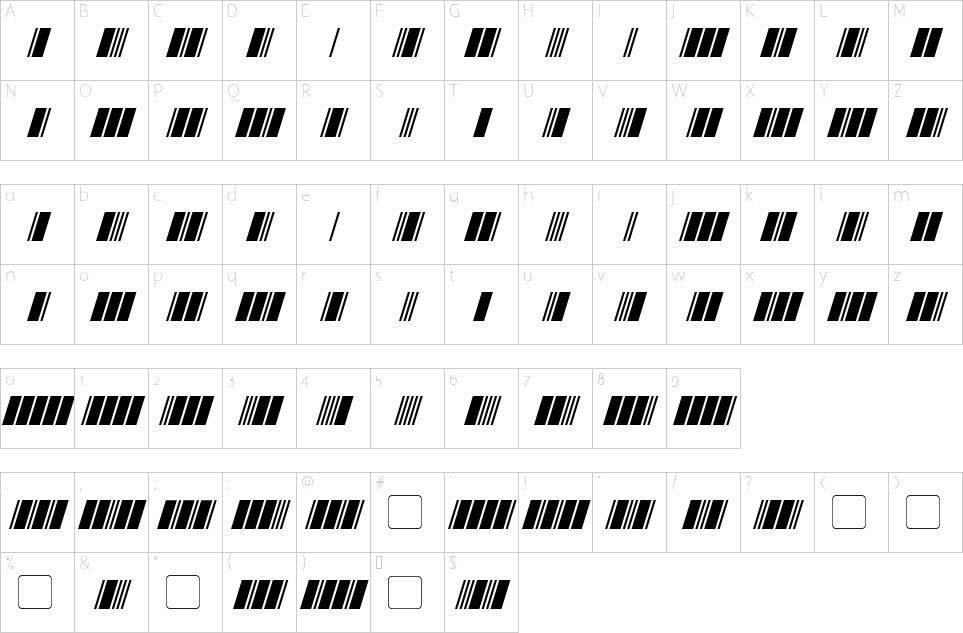
A Morse Tech Font é uma elegante escolha para designers e criadores de conteúdo digitais, especialmente aqueles que buscam uma fonte moderna e minimalista. Criada pelo designer Pixel Sagas – Neale Davidson, esta fonte proporciona um acabamento clean e sofisticado, ideal para aplicativos de notícias, sites de tecnologia e outras plataformas digitais. Seu design minimalista e moderno deixa sua marca de forma contemporânea, garantindo que a sua mensagem seja clara e atraente. A Morse Tech font é uma ótima opção para aqueles que procuram um estilo minimalista e moderno, sem perder a personalidade do texto. Disponível tanto para sistemas Windows quanto para Mac, esta fonte é uma excelente adição para qualquer projeto.